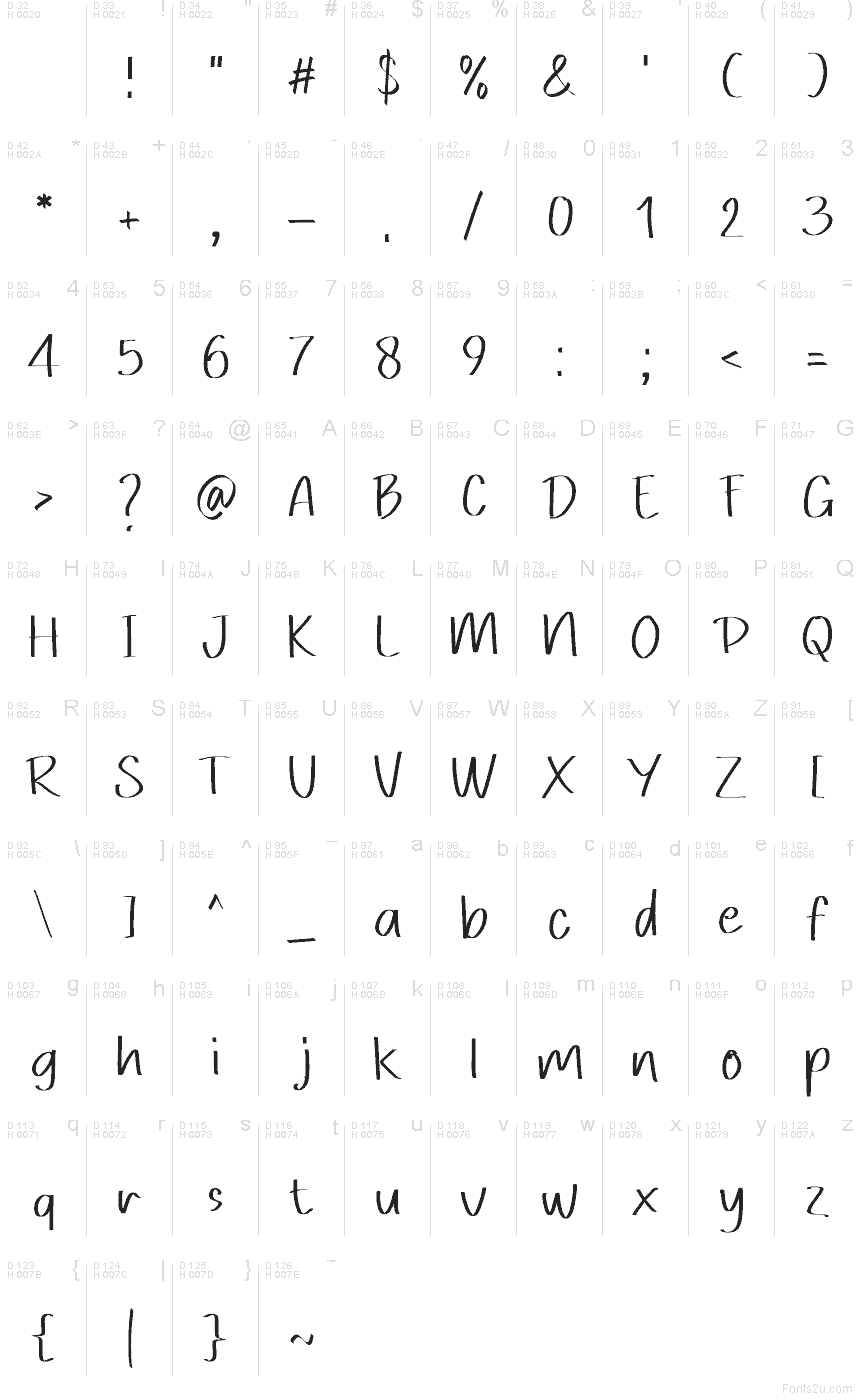
Cooling cartoon
Cooling Cartoon від Hello Good Studio - це безкоштовний рукописний шрифт з високими, вузькими літерами та м’якими, округлими формами. Знаки виглядають вільними, а не жорсткими, з плавним ритмом і легкими нерівностями, які додають тексту невимушеного, живого характеру.
Cooling Cartoon чудово підходить для логотипів, заголовків на плакатах, дитячої упаковки, графіки для соцмереж та запрошень, оскільки його простий «мальований» ритм робить написи приязними, не втрачаючи при цьому структури. Він також ідеальний для коротких підписів та декоративних цитат, де потрібен легкий рукописний акцент.